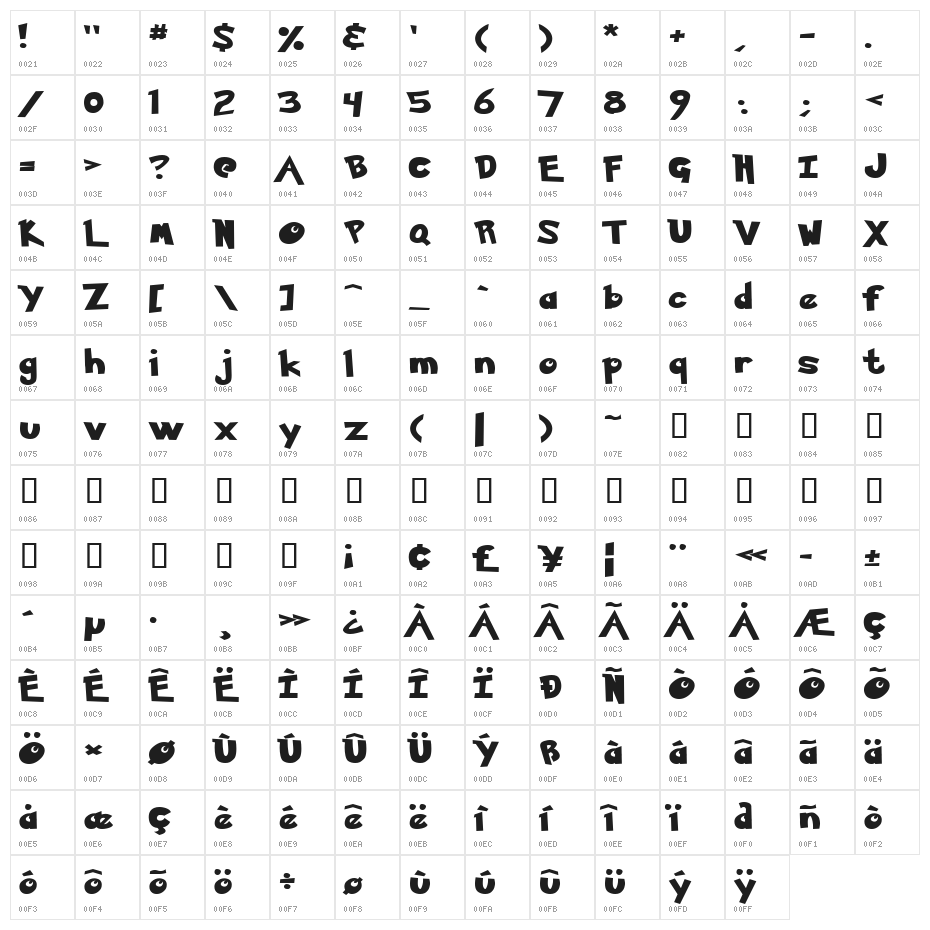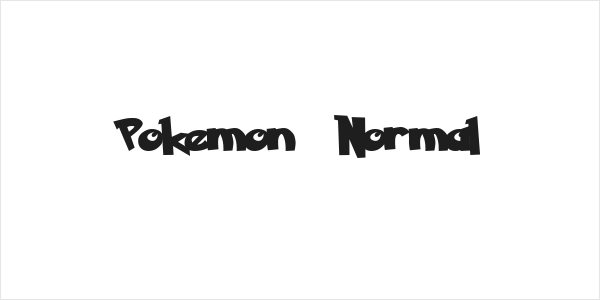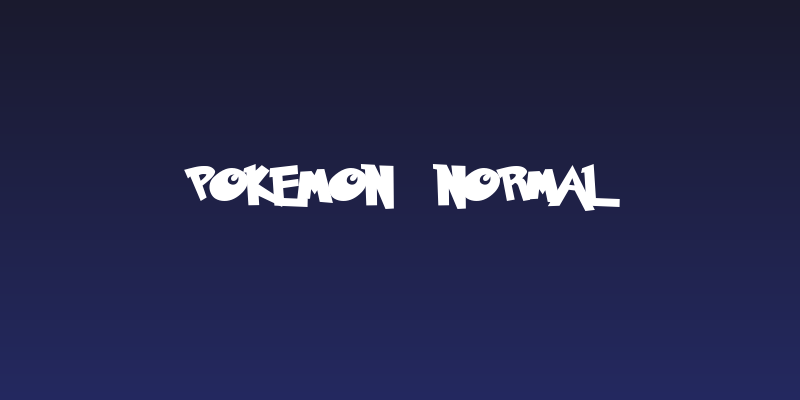
Pokemon Normal Font
| Stile generale | Playful, Cartoon-like |
| Progetti proposti | Ideal for children's book covers, animated movie titles, video game graphics, and playful branding. |